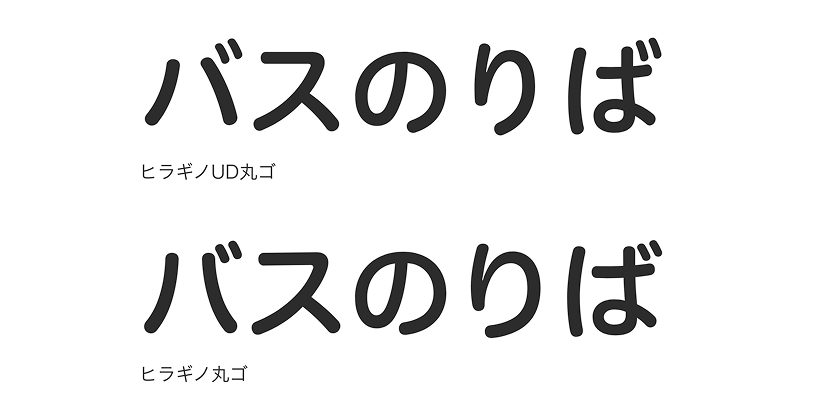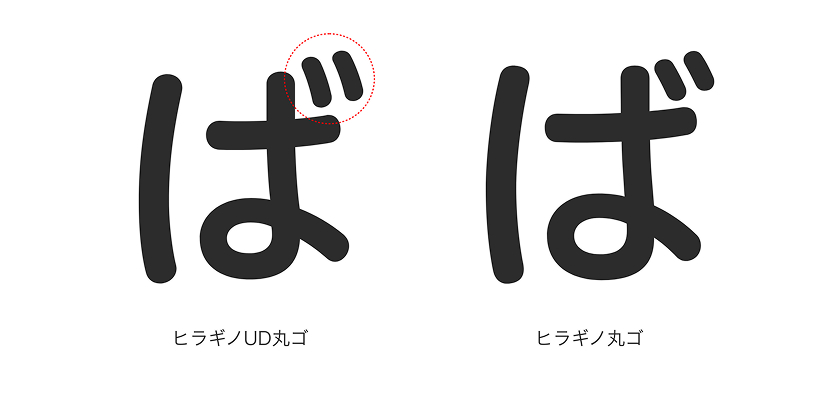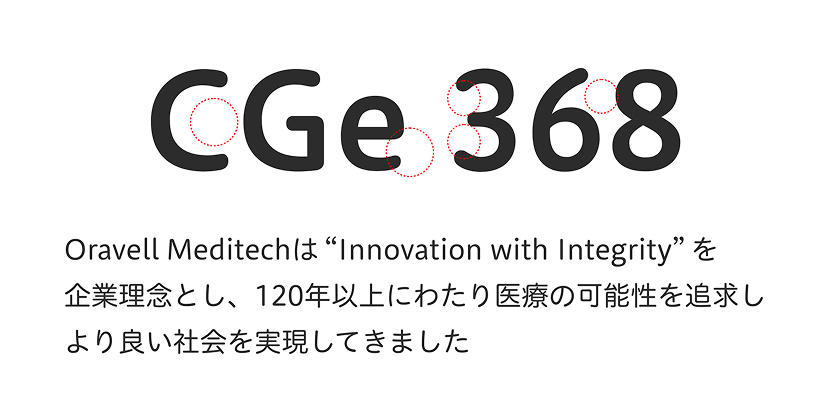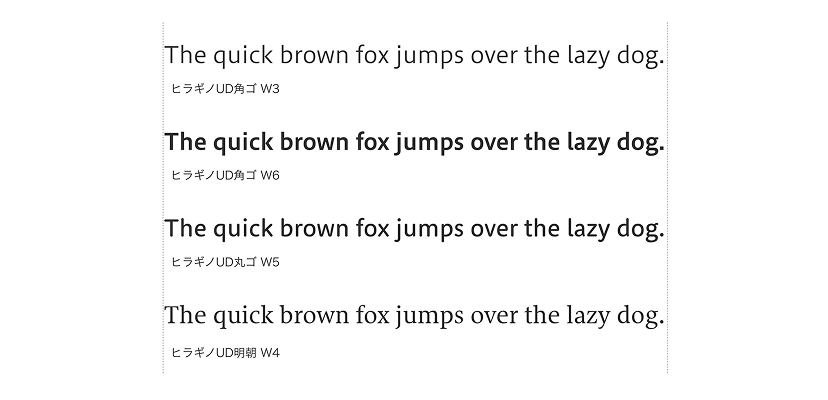
ヒラギノUD丸ゴ
ひらぎのゆーでぃまるご
Hiragino UD Sans Rounded
ひらぎのゆーでぃまるご
Hiragino UD Sans Rounded
ヒラギノUD丸ゴは、ヒラギノ丸ゴの基本デザインを受け継ぐユニバーサルデザインのフォントです。長い文章の読みやすさを求めて、字面をやや小さめにまとめ、仮名には長く読んでも疲れないやわらかな骨格を採用しているため、大きさの異なる漢字・仮名・欧文が文章に自然な抑揚・リズムを生み出し、文字に求められる美しいデザイン性と長い文章も心地よく読み続けられる可読性を提供します。
文字の誤読をさけるため、仮名は濁点・半濁点をハッキリと強調、数字と欧文もヒラギノUDフォントのオリジナルデザインとしました。また、ヒラギノUDフォントは全書体で共通の文字幅を採用しているため、書体やウエイトを変えても同じ行長を維持できます。文字原稿の変更やデザインの改訂などの際、余分な工程を増やすことなく容易に対応していただけます。
雑誌本文、Webデザイン、サインデザイン、テレビテロップなど幅広い用途に対応し、印刷でもディスプレイ表示でも、縦組みでも横組みでも美しい組版を実現します。
ヒラギノUD角ゴ・ヒラギノUD明朝・ヒラギノUD丸ゴは、中庸で「長く/楽に/読ませる」ことを重視しています。一方、ヒラギノUD角ゴFは、ヒラギノの現代的なデザインの印象を引き継ぎ、「くっきりと/見せる」ことを重視しています。
長く読んでも疲れにくい、すっきり柔らかな骨格を採用。ひらがな、カタカナのストロークの先端部分にはやや丸みを持たせ、落ち着いた印象を与えます。
ヒラギノUDフォントの仮名は誤読につながりやすい濁点・半濁点を大きめに修正しています。濁点は点と点の位置を広げ、より明るく読みや取りやすくなっています。
ヒラギノUDフォントの従属欧文は「1」や「7」、「C」や「O」など読み間違えやすい文字の誤読防止に配慮しています。欧文書体単体としても美しく、和欧混植の文章もスムーズに読み進めることができます。
通常は、スタイル(セット・ウエイト)ごとに異なる文字幅とプロポーショナルピッチをヒラギノUDフォント内ですべて共通化。スタイルや太さを変えても組版が崩れません。